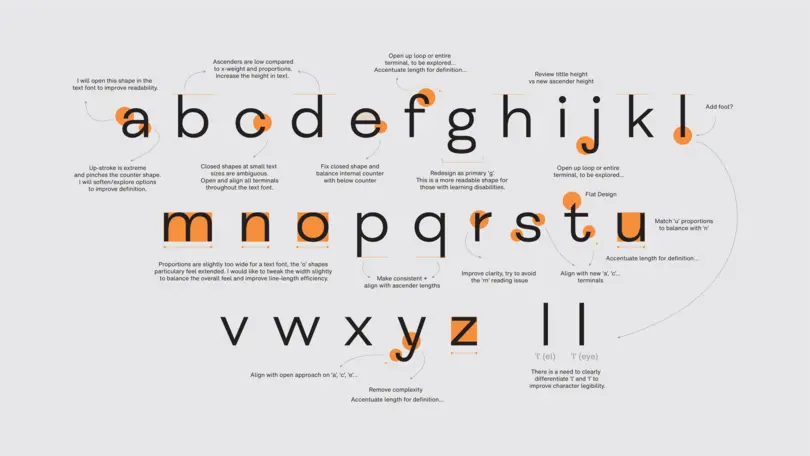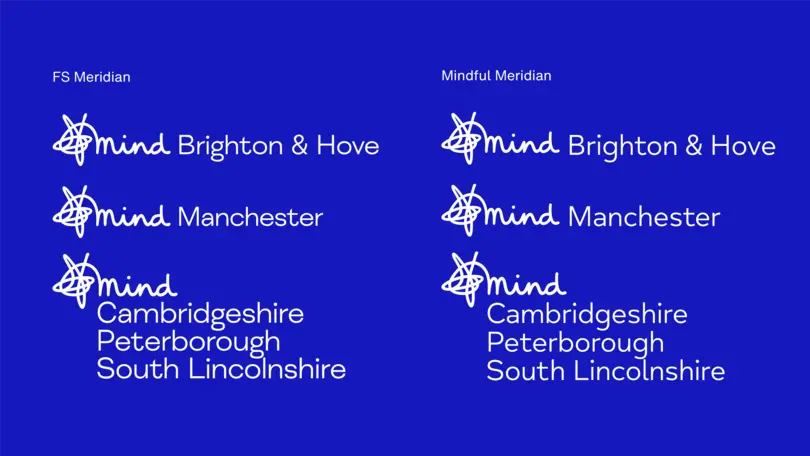
Un nuevo tipo de letra aporta claridad digital al compromiso de Mind con la salud mental.
« En el mundo de la tipografía, la accesibilidad no depende únicamente del diseño del tipo de letra o de la forma de las letras. También influyen en gran medida la aplicación, el color, el contraste y la tipografía en sí. »
Phil Garnham, director creativo de tipografía
Tras años de campañas para crear conciencia e informar sobre la salud mental, a la organización benéfica Mind le llegó el momento de actualizar su célebre identidad visual. El logo del garabato es ampliamente conocido en Inglaterra y Gales, pero las redes sociales y otros espacios digitales exigían cambios a la organización. Monotype Studio desarrolló Mind Meridian en colaboración con la agencia DesignStudio. Se trata de un tipo de letra modificada que convierte la cercanía y la accesibilidad en la esencia de la marca.
El encargo.
«Mind buscaba un socio que la ayudara a mejorar su marca, su historia y su expresión visual, y a comunicarse con el resto del mundo», comenta Vinay Mistry, director creativo de DesignStudio, que trabajó en la actualización de la marca. «Investigamos a fondo el trabajo de la organización benéfica y las experiencias vividas por distintas personas, tanto de la plantilla como de gente voluntaria, y empezamos a comprender ciertos detalles importantes que no estaban funcionando tan bien como los demás».
Mind es la organización benéfica de salud mental más grande del Reino Unido. Antes, usaba varias fuentes con estilos diferentes que había ido adquiriendo a lo largo de los años y que debía adaptar a las exigencias de accesibilidad. Una parte fundamental del encargo de la tipografía y el sistema de diseño nuevos era facilitar el acceso a la variada audiencia con la que trabaja Mind. Además, debía ser fácil de usar por cualquier participante del programa de voluntariado y las organizaciones locales de Mind, aunque no tuviera experiencia con el diseño.
Como ocurre con muchas otras marcas, buena parte de las interacciones de Mind ahora tienen lugar online, lo que hace que el ámbito digital sea absolutamente esencial para llegar a su audiencia. Un objetivo clave era actualizar su paleta tipográfica para comunicarse con claridad en estas plataformas y lograr que transmitiera sus mensajes fácilmente por medio de la tipografía. Además, también era necesario tener en cuenta el valor del logo del garabato de Mind, que siempre ha sido una parte muy querida de la marca.
« Nuestra prioridad era asegurarnos de que fuera muy fácil de usar, por ello creamos un tipo de letra que funcionaba bien en todas partes, tanto online como impresa. Tenía que ser adecuada tanto en tamaños muy grandes, para la señalización y los pósteres, como muy pequeños, por ejemplo, para brindar información a gente que la necesita de verdad. »
Vinay Mistry, director creativo de DesignStudio
Era esencial que el nuevo tipo de letra reflejara la amabilidad y el respeto que caracterizan a Mind. La organización se creó para llegar a las personas y conectar con ellas, y su misión adquirió un nuevo significado ante los nuevos desafíos de salud mental que planteó la pandemia. Como dice Mistry, después de la renovación, la marca debía expresar el mismo nivel de humanidad: «Es necesario que la gente sepa que puede confiar en esta organización directamente, y eso fue una parte esencial del encargo del tipo de letra».
La solución.
DesignStudio ya había desarrollado una nueva paleta de colores que representaría el espíritu de lucha de Mind y que era lo suficientemente adaptable como para transmitir un tono más delicado cuando fuera necesario y otro más dinámico cuando hiciera falta uno con más garra. Esto sirvió para reflejar la magnitud de la misión de Mind, que incluye el apoyo y la defensa de la salud mental para que se refleje en las políticas del gobierno.
El nuevo tipo de letra de la organización se diseñó para ir en sintonía con esta identidad de marca renovada, por lo que mantenía la vitalidad del garabato de Mind y respondía al mismo tiempo a las necesidades funcionales de la organización; en particular a los requisitos de accesibilidad. Mind Meridian es legible para las personas con problemas de visión y está diseñada a medida para que quede bien con las versiones locales hechas a mano del logo de la organización.
«En el mundo de la tipografía, la accesibilidad no depende únicamente del diseño del tipo de letra o de la forma de las letras», explica Phil Garnham, director de tipografía de Monotype. «También influyen en gran medida la aplicación, el color, el contraste y la tipografía en sí. Hemos colaborado para definir un conjunto de reglas claras al respecto».
«Una cosa que aprendimos de Monotype fue que alinear la tipografía a la izquierda o usar un kerning o un interlineado determinados puede ayudar mucho a hacer que el texto se lea mejor». «Además de las formas y los caracteres en sí de la fuente, esa idea fue de gran ayuda».
FS Meridian fue el punto de partida del diseño. Junto con DesignStudio, el equipo de Monotype Studio analizó las formas de sus letras y los espacios, y añadió cambios sutiles. Por ejemplo, estrechó las proporciones, abrió los espacios entre caracteres, amplió las ascendentes y acentuó las terminaciones, todo ello para lograr que la tipografía tuviera «más aire» y pudiera leerse mejor. Estas modificaciones se basaban en las amplias investigaciones sobre accesibilidad que ya había hecho Monotype para marcas como ING, RNIB y Mencap.
Mind Meridian se ajusta la situación actual de la marca y le permite adaptar su tono al futuro. De ese modo, podrá seguir luchando por la salud mental sin perder ni un ápice del valor pasado de su marca, que es objeto de cariño y confianza para mucha gente.